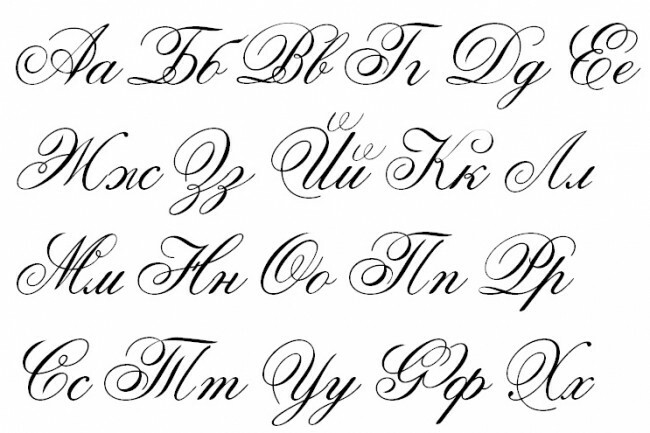
Красивый шрифт букв русского алфавита для оформления: Красивые буквы русского алфавита печатные и прописные для оформления плакатов, стендов, праздников, Дня рождения, Нового года, …
Красивые шрифты для онлайн сервисов — это наборы символов из таблицы Юникод, подобранные по внешнему виду и разделённые на отдельные части. Кто-то называет их красивыми шрифтами, кто-то алфавитами, но по сути это наборы букв из одной таблицы с разной стилизацией. Эти символы соответствуют по написанию стандартному английскому алфавиту или латинице, но часть слов этими буквами можно написать и на русском языке. Таких красивых шрифтов насчитывается порядка 10 штук, и все можно использовать в популярных социальных сетях: Tik Tok, Likee, VK, Instagram, Одноклассники.
Шрифты на русском или английском?
В таблице юникод, есть только один шрифт русского языка (стиль начертания).
Все остальные русские шрифты образуются путём замены на буквы из других алфавитов, схожих по начертанию. Поэтому часть текстов не могут быть написаны на русском используя некоторые из наборов букв, они переводятся на латиницу и только тогда на красивые шрифты.
С английским языком всё проще. Шрифты для английского (латиницы) алфавита присутствуют во множестве. Поэтому ники имена и другие короткие тексты удобно оформлять именно латиницей.
- Dosis
- Libre-Baskerville
- Abril Fatface
- KoHo
- Helvetica
- Cormorant
- League Spartan
- Poppins
- Playfair Display
- Raleway
- Lora
Шрифт для презентации №1: Lato
Мы все видели миллионы презентаций с использованием стандартных шрифтов, таких как Arial и Times New Roman. И хотя Lato во многих случаях по-прежнему используется по умолчанию, этот шрифт без засечек имеет более современный вид.
Кроме того, разнообразие вариантов начертания Lato — от тонкого до полужирного, жирного и других — повышает общую привлекательность этого шрифта.
Этот шрифт можно использовать по-разному, как вы увидите в шаблонах презентаций ниже.
В приведенной ниже презентации шрифт Lato используется в качестве заголовка на каждом слайде. Он используется в паре с более плотным шрифтом с засечками, что обеспечивает хороший баланс между ними.
Вот еще один пример презентации с использованием Lato в качестве основного заголовка. В обоих случаях используется шрифт Lato Light для создания более элегантного и современного вида слайдов.